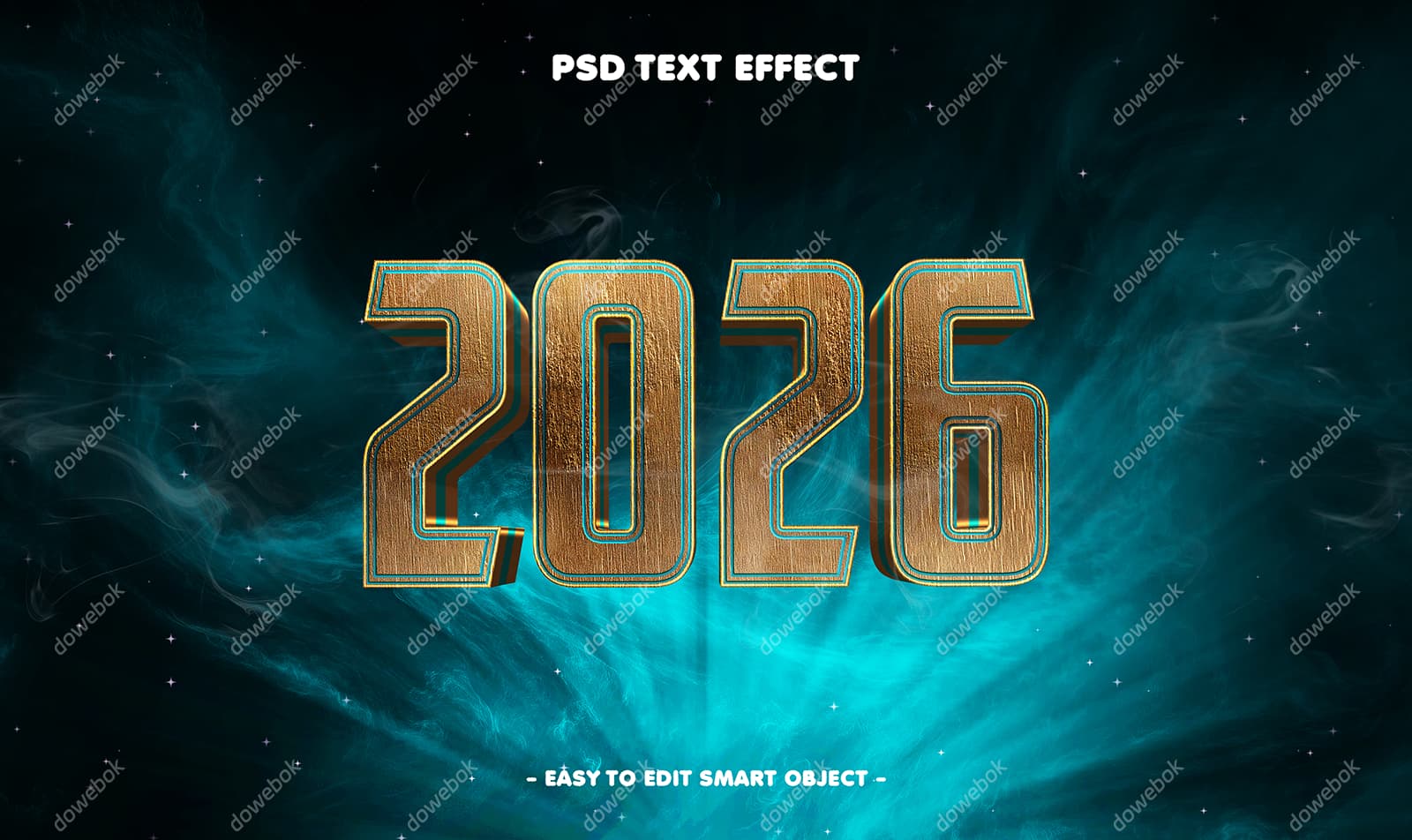
这是一款由金色立体数字设计的 2026 新年快乐 PSD 素材,暗调背景衬着青蓝射线与星光烟雾,“2026” 以铜纹立体字呈现,边缘镶浅金,质感复古且富有金属张力。顶部标 “PSD TEXT EFFECT”,底部注其为可编辑素材。整体铜青配色既显复古高级感,又借烟雾元素添朦胧氛围,既突出字体效果的质感,也点明可编辑属性,适配复古风创意海报等场景。